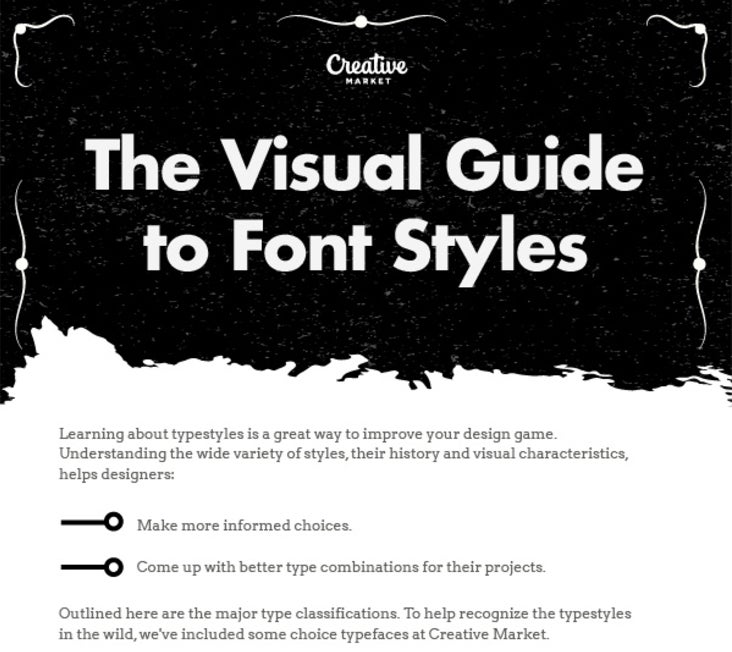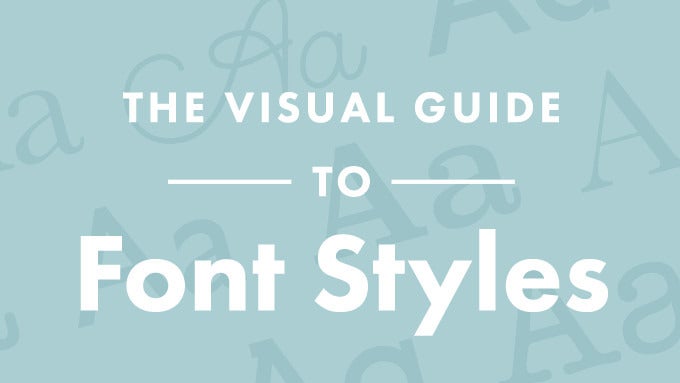
Typografie-Basiswissen für Web-Designer: Dieser Guide gibt dir einen Crash-Kurs
Worin liegt der Unterschied zwischen „Serif Type Styles“ und „Sans Serif Type Styles“? Dieser Typografie-Guide erklärt Stile und ihre Besonderheiten.
Typografie-Guide erklärt Stile und ihre Besonderheiten. (Grafik: Creative Market)
Die Font-Stile und dazugehörigen Schriftarten zu kennen, ist nicht nur für Typografie-Designer von Vorteil. Auch Web-Designer profitieren davon. Das Basiswissen zu den visuellen Charakteren der Fonts und ihren Wirkungen hilft dabei, noch besser entscheiden zu können, welche Schriftarten einem Projekt gut stehen. Und natürlich auch, welche Schriftarten sich hervorragend kombinieren lassen.
Dieser Typografie-Guide erklärt Stile und ihre Besonderheiten
In einer Infografik präsentiert Creative Market jetzt wissenswerte Informationen zum Thema. Der Design-Blog erklärt unter anderem Stile wie „Serif Type Styles“, „Sans Serif Type Styles“ und „Script Type Styles“ und stellt Unterarten dieser Kategorien sowie dazugehörige Fonts vor. Zum „Transitional“-Stil gehören beispielsweise berühmte Schriftarten wie „Times New Roman“ und „Georgia“ – die übrigens auch in Bewerbungsschreiben ihre ganz eigene Sprache sprechen.
Dieser Typografie-Guide lässt keine Fragen offen. (Infografik: Creative Market)